ที่จริงก็แค่ผลิตสื่อไว้ใช้เอง ไม่มีได้มีอะไรมาก
แต่บางตัวก็ทำเพราะอยากทำเล่น ๆ บ้าง
เช่นฟอนต์ การฟีจี่ที่ทำไปนั่น เป็นต้น
เมื่อเทคโนโลยีมันทันสมัยเราใช้มันให้เกิดประโยชน์บ้าง
แต่ไม่ใช่บริโภคนิยมแบบไร้ปัญญาอะไร
New font
โลโก้นี่ออกแบบไว้ว่าจะใช้ในการทำกองทุนการศึกษาของลูกเณรเลยน่ะเนี่ยะ เอามาลงแปะไว้ซะงั้น  กร๊าก
ลองพิมพ์เล่นดู แต่มันอ่านยากนิดโหน่ย
สงสัยเพราะทำฟอนต์กราฟีจี่แน่เลย หรือไม่ก็เพราะฟอนต์อรุณวิลาศ มนุษย์โลกธรรม กร๊าก กร๊าก กร๊าก
ตอนนี้คิดว่าพอและ
เอาเวลาไปทำรายงานละน่ะไม่ทำฟอนต์เพิ่มล่ะ
ว่างก็จะปรับและตรวจแก้บางฟอนต์ให้มันดีขึ้นแล้วก็ปล่อย
หรือไม่  ต่อไปถ้าจะทำจะพยายามให้เป็นฟอนต์มาตรฐาน
ไม่ทำเล่นอีกแหละ ที่ทำเล่น ๆ มาเพราะแค่ทำเพลิน ๆ ไม่ได้คิดนึกถึงหลักการอะไรมาก
ใช้แค่ Perception พื้น ๆ ผสมกับความนึกชอบใจธรรมดา ๆ เท่านั้น
อย่างที่บอกคือ วัตถุประสงค์หลักของการทำฟอนต์หลวงพี่แค่หัดทำอุปกรณ์ที่จะใช้ในการสื่อสารกับสังคม
บางตัวก็ทำเล่น ๆ ดูขัดตาขัดใจกับพฤติกรรมตนเองก็ช่างมัน ไม่ได้คิดอะไร
แล้วจะมาปล่อยให้ใช้วันหลังนะครับ รอคิวอยู่(ยังไม่ได้จอง เพราะยังไม่ได้ตรวจแก้บางตัว)
ตัวตูมตามนั่นเจ๋งมากครับ น่ารัก เจ๋ง
ตอนที่ทำ "ตูมตาม" คิดแต่จะทำให้มันออกแนว Graffiti
สังเกตที่ตัว Eng. ที่ทำ เพราะเริ่มที่ตัวละตินก่อนแล้วก็มาทำไทย
แต่พอทำไปมันไม่ออกแนวนั้น ก็เลยทำไทยแบบไทย ๆ เลย
และคิดว่าไปปรับตัวละตินใหม่ และก็ทำตัวไทยใหม่ขึ้นมาอีกชุดเลย
เมื่อคืนเผลอไปกดการลากเส้น ก็คิดว่าท่าทางจะต้องทำฟอนต์เล่นด้วย แต่ให้น้อยลง
ทำฟอนต์มาตรฐานให้มากขึ้น
และเมื่อคืนนี้เองก็ ปรับฟอนต์(ข้างล่าง)เพื่อจะเข้าคิวปล่อย
ตัวละตินยังปรับไม่เสร็จน่ะ คิดจะปล่อยแต่รอคิวก่อน
เพราะช่วงนี้มีฟอนต์ใหม่มาให้ปล่อยรอเยอะอยู่
คิดว่าจะปล่อยเดือนละสามตัว แต่ต้องทิ้งห่างเวลาบ้าง
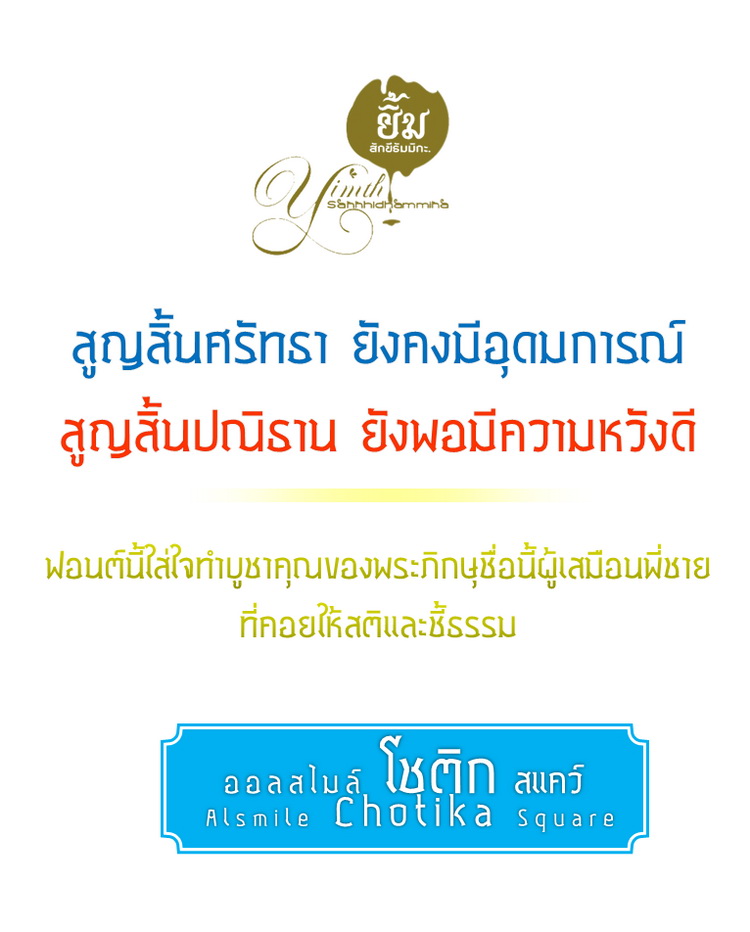
วันนี้เข้าไปดูฟอนต์ของดีบี เห็นเอาชื่อนี้ที่เราคิดเล่น ๆ
ไปทำเป็นชื่อฟอนต์(ขาย)จริง ดีใจนะเนี่ยะ มีคนคิดชื่อฟอนต์ได้ตรงกัน   กร๊าก
จำได้มั๊งป๊าวที่หลวงพี่ทำฟรีวิวฟอนต์ช่วงแรก ๆ โน้น มีฟอนต์ชื่อนี้อยู่